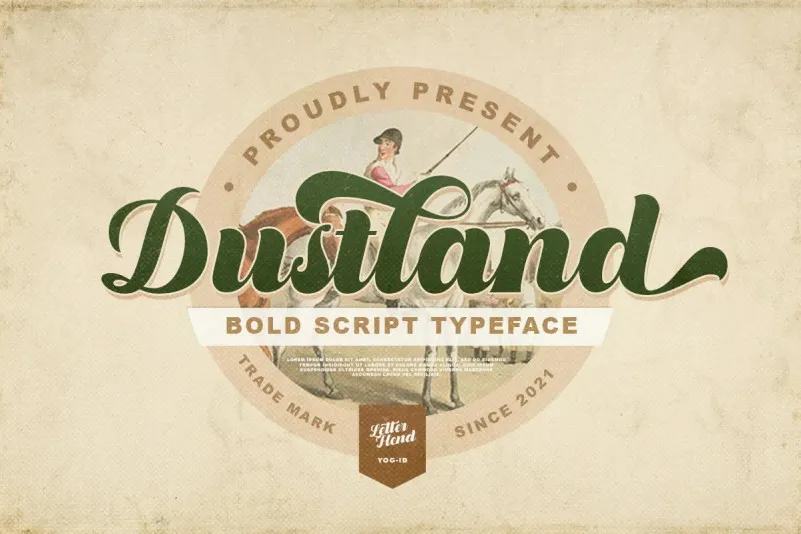
A fonte Dustland Bold Script é perfeita para quem procura uma tipografia que transmite sofisticação e modernidade no mesmo instante. Desenvolvida por 99designs, esta fonte bold é baseada num estilizado script clássico, com um formato atraente que destaca-se do resto da galera. Ideal para aplicação em logotipos, headlines, rótulos e diversos outros formatos formais como convites, selos, marcas, revistas, livros, cartões de agradecimento ou casamentos, embalagens, moda, maquiagem, materiais de escritório, livros, selos ou qualquer tipo de publicidade. Com suas linhas sólidas e elegantes, Dustland Bold Script é perfeita para quem busca uma fonte moderna capaz de manter a formalidade sem perder a sensação de sofisticação. Seja você um designer gráfico profissional buscando um estilo único ou alguém que simplesmente adora criar layouts e materiais de marketing com estilo, Dustland Bold Script é definitivamente o tipo de fonte que você precisa para dar aquele toque especial aos seus projetos.